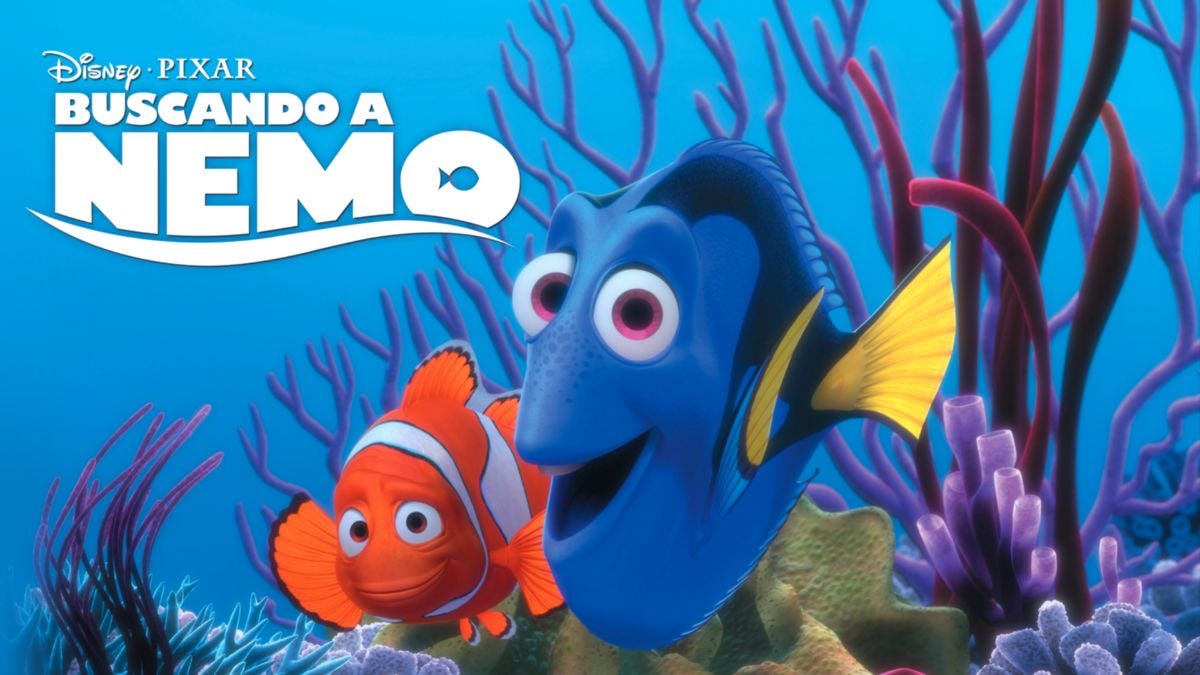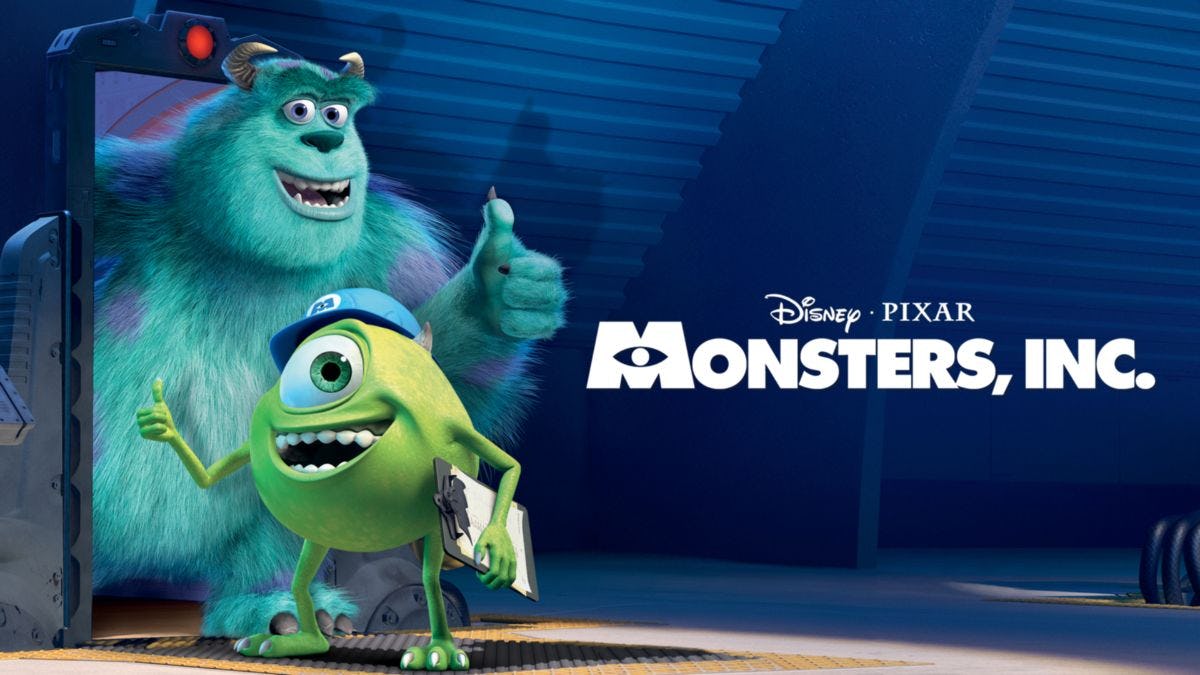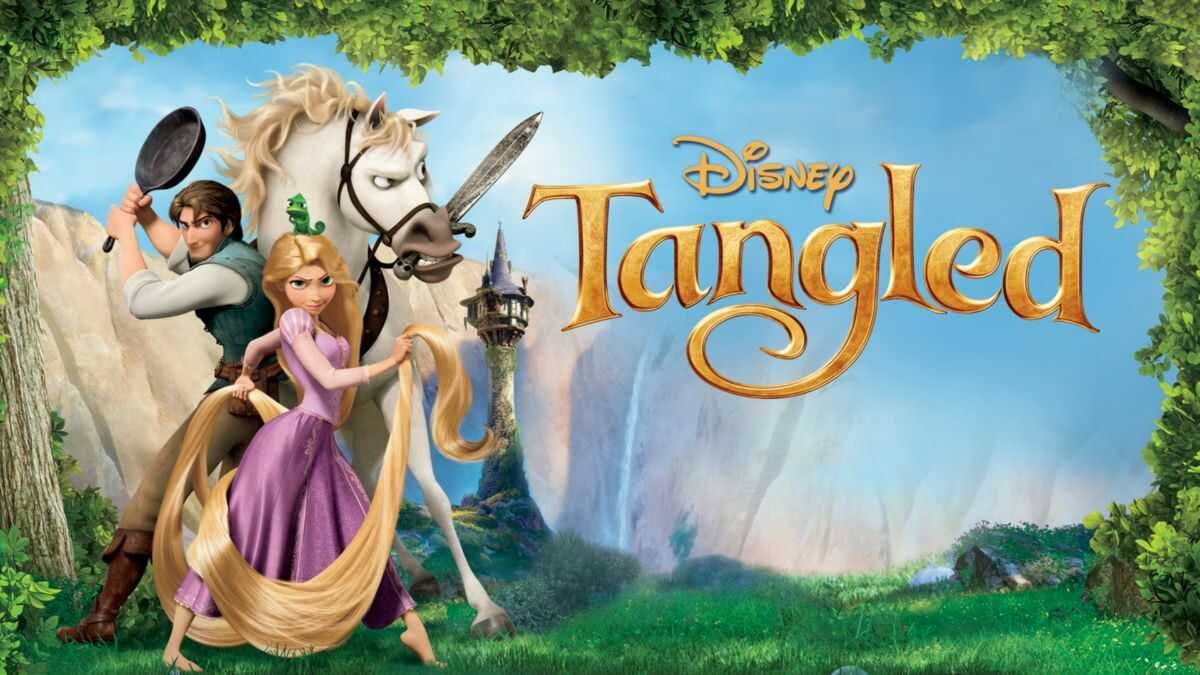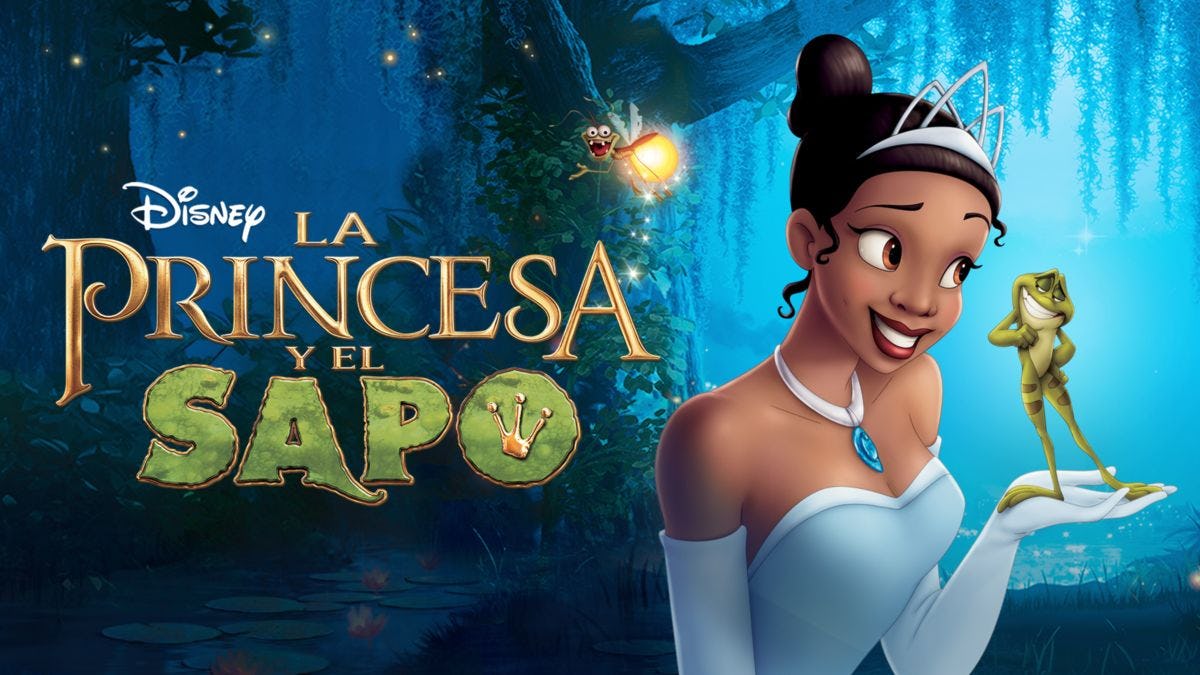
Las tipografías de Disney que acompañan nuestros días
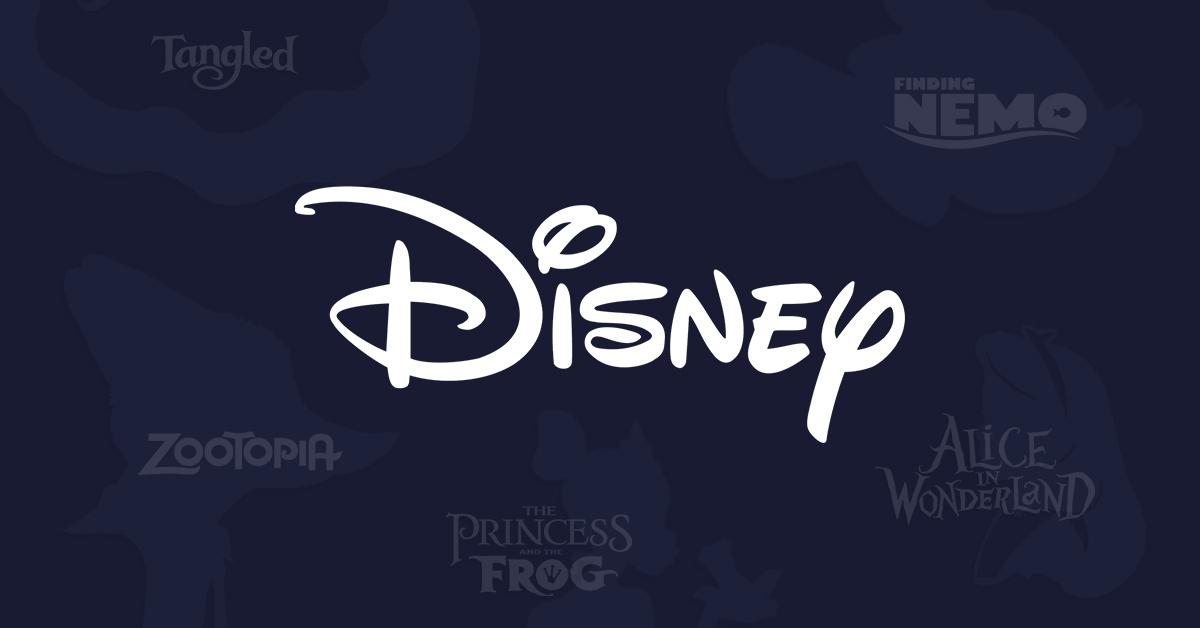
Castillos, hadas, películas e historias geniales, ¿te suena a Disney? No importa la edad que tengas, todos se han emocionado con Buscando a Nemo o Alicia en el país de las maravillas. Como sabemos que quieres ver tu nombre con las tipografías de Disney, en este artículo conocerás las letras de Mickey Mouse, Zootopia y más.
Y, si eres diseñador, más temprano que tarde te tocará un cliente que te pedirá la “fuente Disney”. Así que, lo mejor es estar preparado siempre.
Ahora sí, a buscar a Nemo, digo, a conocer las tipografías de Mickey Mouse.
¿Por qué son importantes las tipografías de Disney?
Disney es una súper empresa que está en todas. Tiene canales de televisión, produce películas y ofrece un servicio streaming. En sus inicios, la empresa fundada por Walt Disney, dedicó sus esfuerzos a la animación, diseño de personajes y a darle identidad a sus creaciones. En esta tarea fueron fundamentales las letras y tipografías de Disney.
Con el paso de los años, cada película animada tenía características que la hacían única. Por eso, se hicieron muy conocidas y solicitadas las tipografías de las películas de Disney. Con cada estreno, los seguidores aumentaban y las letras de Disney se hacían mundialmente famosas.
De esta manera, en cada producción que Disney prepara no deja nada al azar. El diseño del abecedario de Disney y sus películas es importante para que los fanáticos cada vez sean más.
Lista de las tipografías de las películas de Disney
- Disney
- Tangled
- Buscando a Nemo
- Zootopia
- La princesa y el sapo
- Alicia en el país de las maravillas
- Aladdin
- Moana
1. Disney
Sin duda, la tipografía de Disney es una de las más reconocibles a nivel mundial. Toda persona que piensa en películas animadas de inmediato trae a su cabeza a Mickey Mouse, el castillo y la fuente de Disney.
Los trazos gruesos y curvos, como hechos a mano, son el sello de esta casa casa editorial. La letra D con extensiones curvas, inmediatamente trasladan a todos a las películas animadas y clásicas. Los profesionales del diseño buscan “tipo de letra Disney” porque siempre hay un cliente que quiere dar una sorpresa a alguien.
Si eres seguidor de Disney o un diseñador que debe hacer un súper trabajo y quieres saber cómo se llama la tipografía de Disney, el nombre es Waltograph. Pero, si estás diseñando la identidad visual de un emprendimiento, revisa estas tipografías para logos y entrega un trabajo asombroso.
A menudo, muchas personas le dicen “letra de Mickey Mouse”, así que no te sorprendas si te piden un diseño con esa tipografía.
2. Tangled
Conocida en español como “Enredados”. Tangled es una producción animada y musical basada en el cuento de Rapunzel de los hermanos Grimm. Lógicamente, hubo un proceso de creación de esta tipografía de Disney.
Entre todas las letras y tipografías de Disney, la de Tangled es especial porque genera la impresión de ser un cabello extenso. Lo decimos por el color, el grosor y los giros que arreglan y dan suavidad a esta fuente de Disney.
Además, es fácilmente reconocible porque la película fue muy exitosa y tiene muchos seguidores. Es más, estamos seguros que en algún momento viste una fiesta infantil con motivos de “Enredados”, donde en el centro de la reunión estaba el nombre de la niña escrito con la letra Disney de Tangled.
Con el fin de ayudarte en tu búsqueda de “tipografías de Disney para descargar gratis”, tenemos esta fuente para ti.
Fuente: brett jordan CC
Para hacer un diseño con este tipo de letra de Disney, descarga Tangled y procura no enredarte entre las capas de tus diseños.
3. Buscando a Nemo
Tú también quisiste ayudar a Marlín a buscar a Nemo, reíste con Dory y te aprendiste la dirección de Sidney. Buscando a Nemo fue una película que envolvió a todos con una historia que atrapa de principio a fin. Nuevamente, las tipografías de las películas de Disney formaron parte de todo el impacto que generó el film.
Sin duda, con un solo vistazo al nombre de la película, la fuente de Disney llama poderosamente la atención. Letras grandes, gruesas y celestes nos trasladan al océano, lugar donde se desarrolla la trama de la película.
Además, todos conocen a alguien tan extraño y divertido como Dory, ¿no es genial esta peli? Así que, no te sorprendas si te topas con un seguidor de Nemo y quire su nombre. Lo que debes hacer es descargar la tipografía de Disney, que fue la casa productora que nos trajo esta súper película animada.
Fuente: Rachel Hisko
Si buscas esta fuente de Disney para copiar y pegar, te informamos que tendrás que demorarte un par de segundos más. Descarga Findet Nemo e instala la letra de Disney en tu ordenador y ahora sí empieza a hacer diseños espectaculares.
Si te gusta la navegación, los barcos y ver una buena historia estamos seguros que Moana es para ti. Y si eres un seguidor de la película y buscas la tipografía de Disney que hizo para esta producción, no busques más porque la tenemos aquí.
Ahora que conoces las tipografías de las películas de Disney, podrás hacer diseños de impacto con referencias a films para toda la vida.